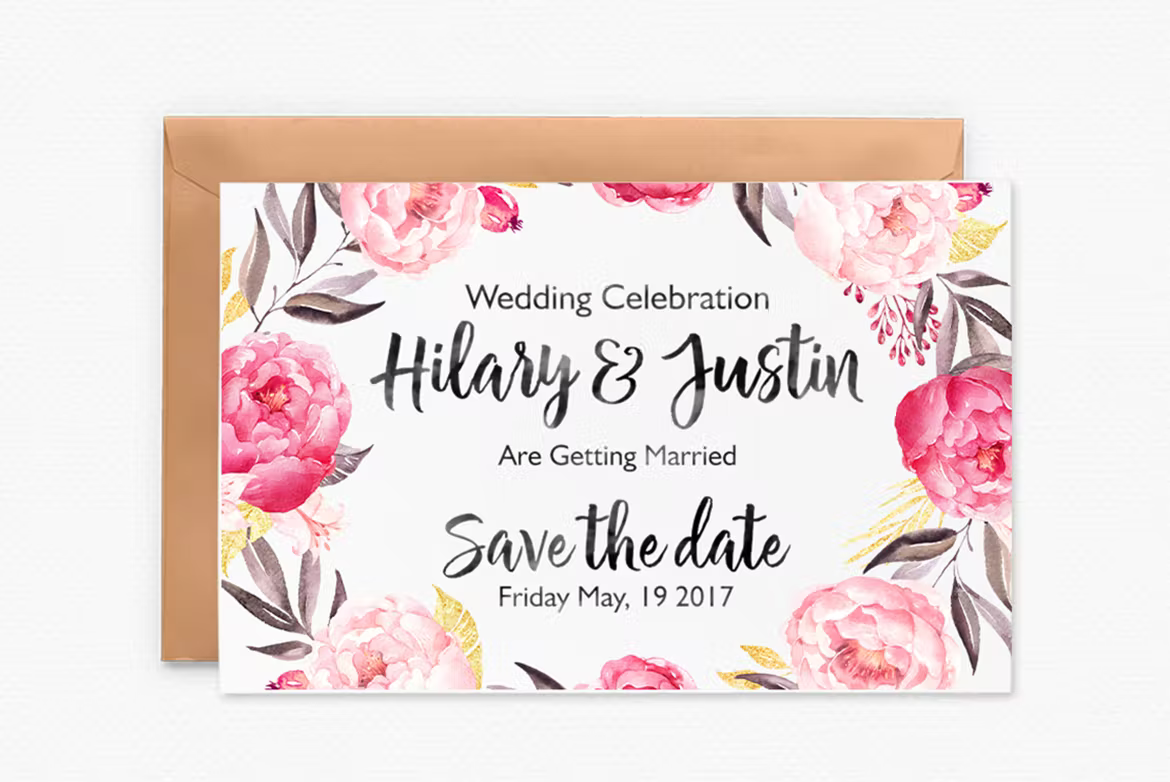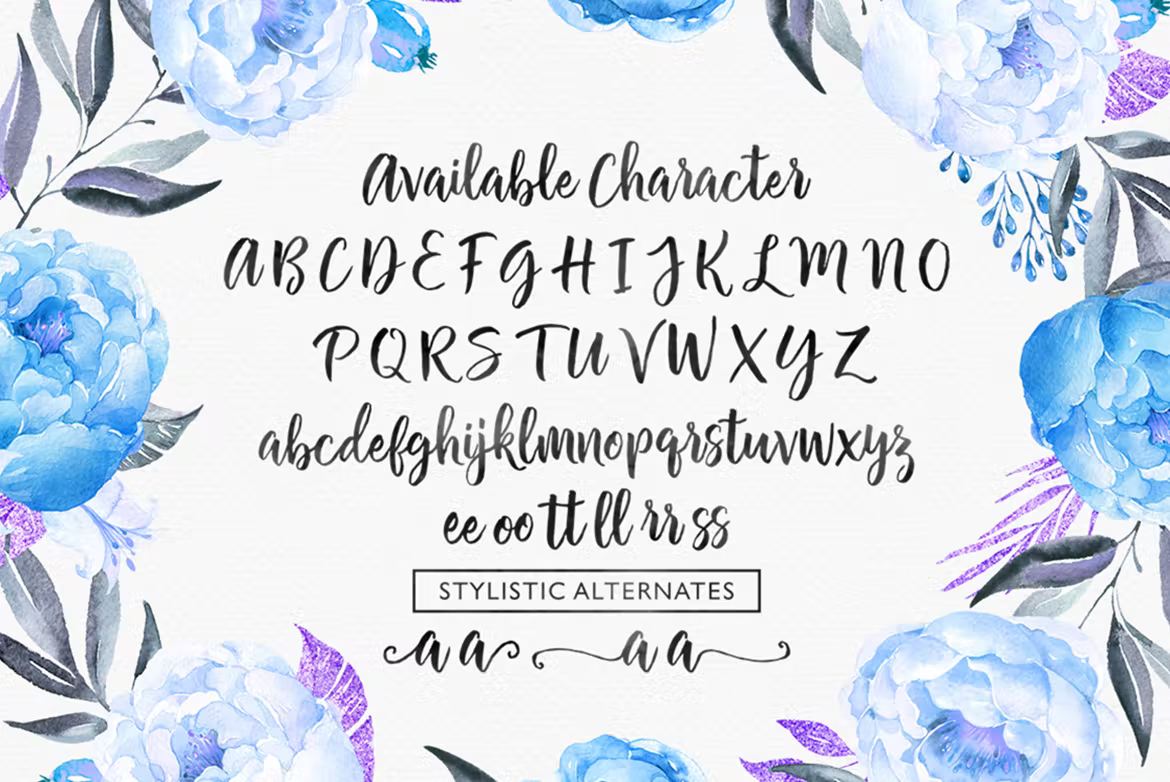
Chamelia Script Font
Chamelia Script est une calligraphie d’écriture moderne, dynamique et jolie avec des swashes. Peut être utilisé à diverses fins. tels que le titre, la signature, le logo, les invitations de mariage, le papier à en-tête, la signalisation, les étiquettes, les newsletters, les affiches, les badges, etc.